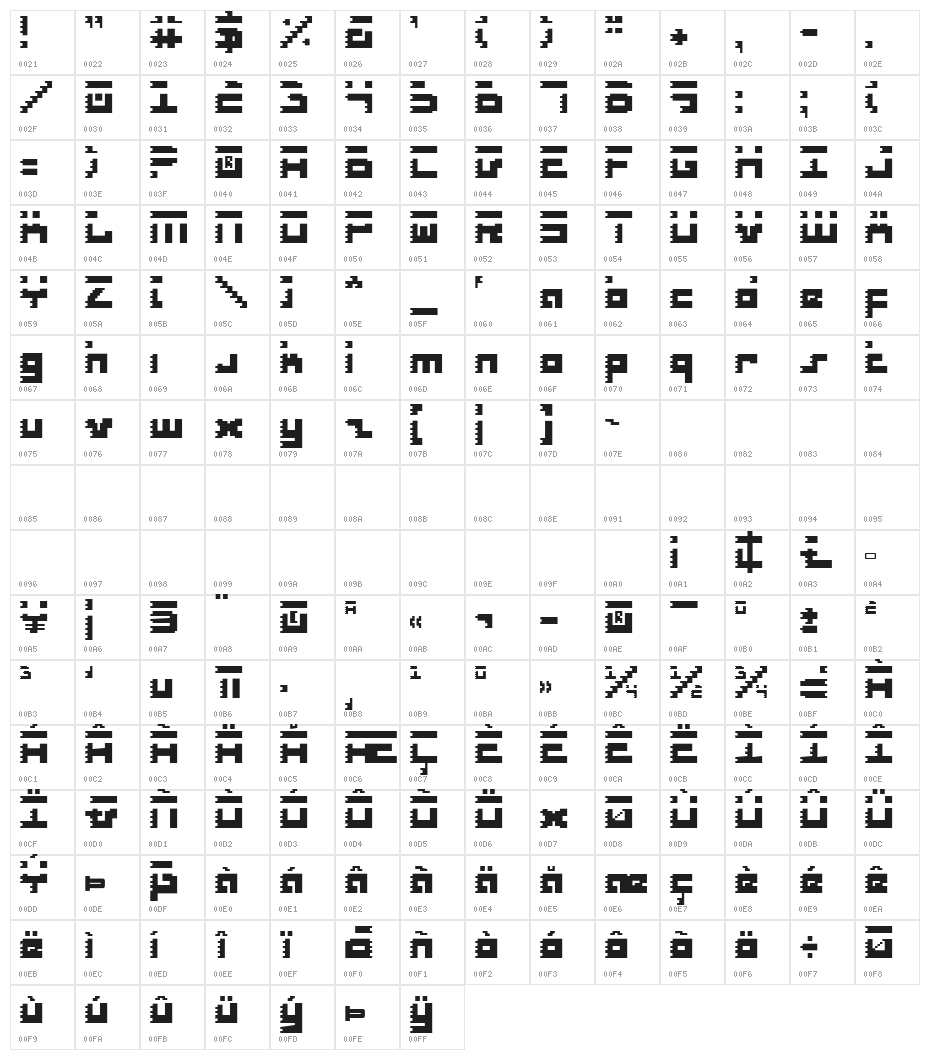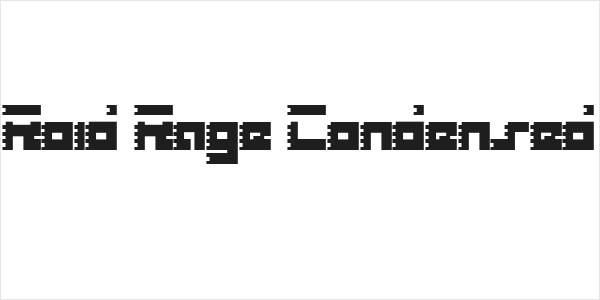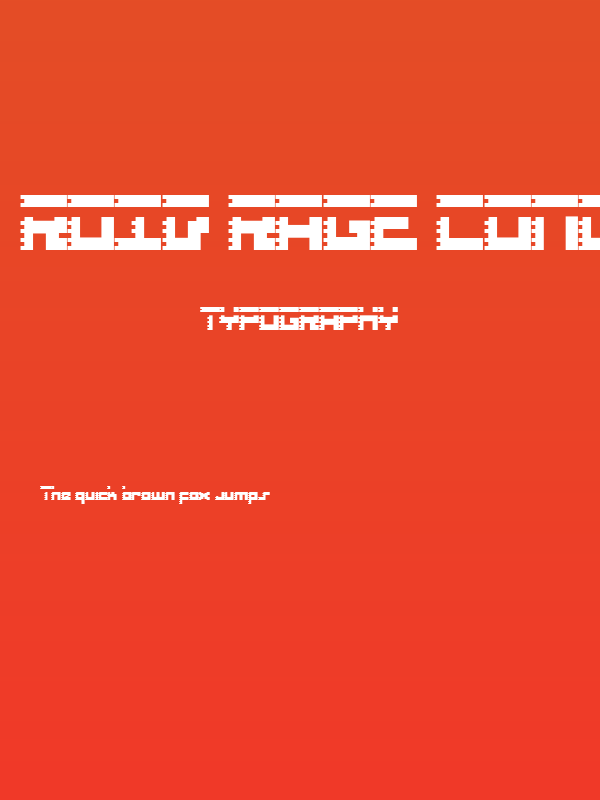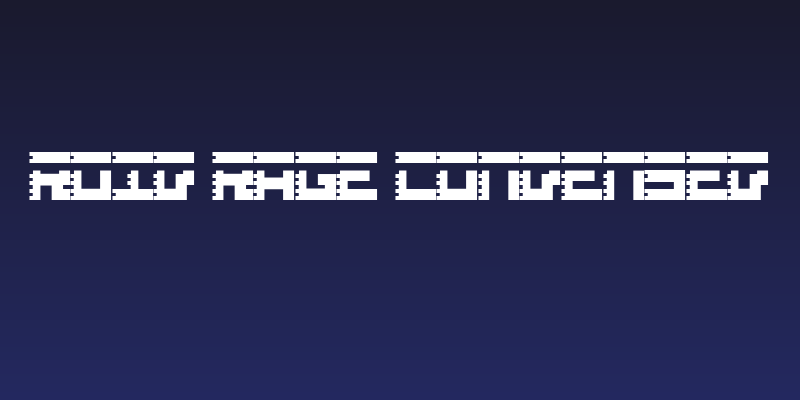
Roid Rage Condensed Font
| Stile generale | Retro, Digital |
| Progetti proposti | Ideal for retro video game designs, digital art projects, tech-themed posters, and any creative work that requires a bold, digital aesthetic. |